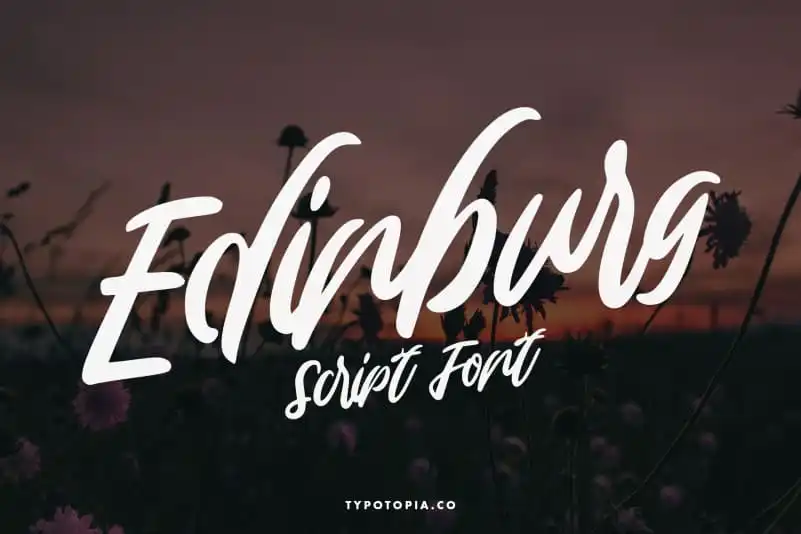
Edinburg Script Font
Descubra Edinburg Script Font na categoria das fuentes de script para adicionar um toque moderno e casual a seus projetos. Essa elegante fonte de calligrafia apresenta uma aparência sofisticada, perfeita para destacar o estilo individual em seu design gráfico. Composta por linhas finas e traços delicados, Edinburg Script é ideal tanto para textos legíveis quanto para elementos decorativos que dão vida ao texto. Ideal para designers buscando um equilíbrio entre estilos tradicionais e modernidade, esta fonte é perfeita para criar layouts elegantes e personalizados. Desde subtítulos engraçados até texturas de logotipo, Edinburg Script é uma escolha confiável para qualquer projeto visual. Caso deseje explorar mais opções ou seja um designer em busca de novos elementos para seus projetos, esta fonte é definitivamente uma opção a considerar. Sintam-se à vontade para experimentá-la e descobrir como Edinburg Script pode ajudá-los a expressar seu estilo personalizado. Seja você criando materiais online ou impressos, Edinburg Script certamente irá tornar seus projetos ainda mais originais e autênticos.